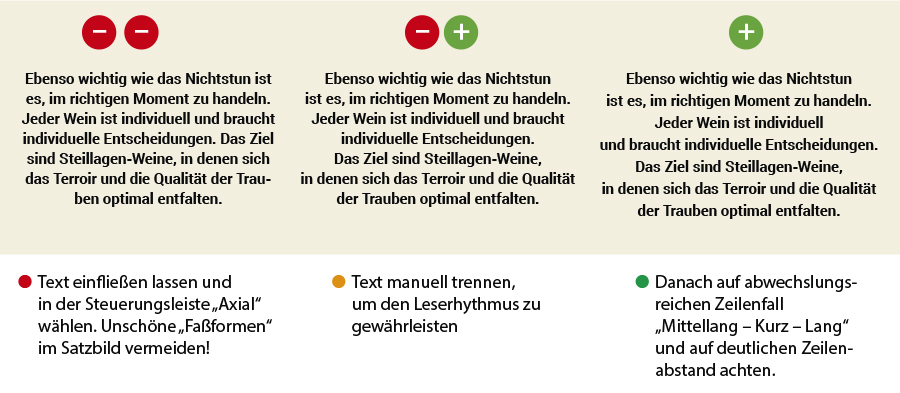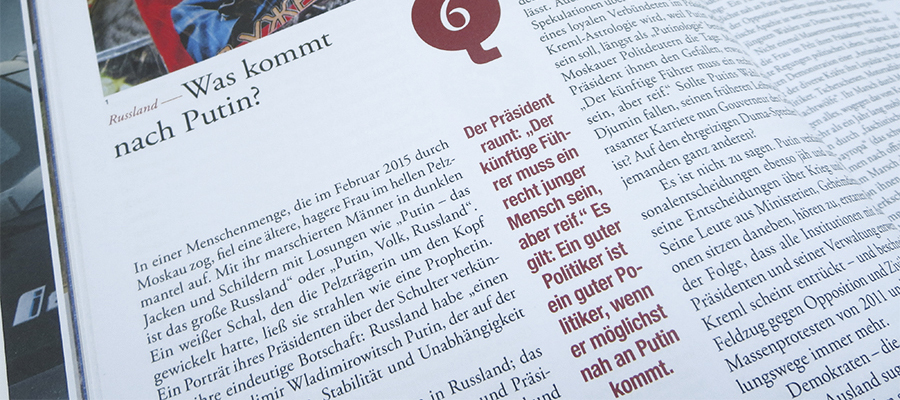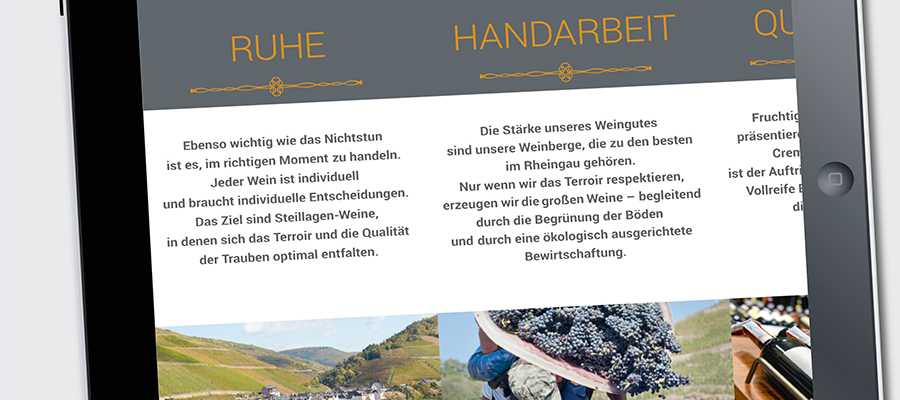
Typografie-Tipps: Axialsatz richtig anwenden und Zeilenfall optimieren
Axialer Zeilenfall in der Stuttgarter Opernzeitung
Ist Ihnen schon mal aufgefallen, dass die axiale Satzart wieder an Bedeutung gewinnt –insbesondere im Magazin-Design? Dabei dachte ich, die eher konservativ anmutende Satzart wäre seit den 70er-Jahren längst ausgestorben (in meiner Zeit als Schriftsetzer habe ich die Satzart oft angewendet, vor 30 Jahren erfreute sie sich großer Beliebtheit). Bis vor kurzem schien der axiale Satz der Gestaltung von Vereinsurkunden, Inhaltsverzeichnissen von Büchern oder dem Gedichtsatz vorbehalten. Aber nein, er ist wieder auf dem Vormarsch, wie das obige schöne Beispiel aus Reihe 5, dem Magazin des Staatstheaters Stuttgart, zeigt!
Dabei hat die Satzart auch durchaus ihre Berechtigung; bringt sie doch Aufmerksamkeit und Abwechslung ins Design. Aber Vorsicht: Bei der Anwendung des Axialsatzes sollten zugunsten der Lesbarkeit und eines ausgewogenen Satzbildes einige typografische Regeln beachtet werden.
Beispiele für axialen Zeilenfall
Gelungener Axialsatz in der Magazingestaltung für eine Tablet-App; Weingut Laquai
Beispiel gelungener Axialsatz in der Magazingestaltung für eine Tablet-App
Schön gestaltet, aber etwas schwierig zu lesen: Sinngerechtere Trennungen, zum Beispiel nach den Satzzeichen, hätten die Lesequalität deutlich verbessert; Quarterly, Frankfurter Allgemeine
Axialer Zeilenfall in einer Randspalte: Schön gestaltet, aber schwierig zu lesen.
Definition Axialsatz
Die korrekte typografische Bezeichnung ist Axialsatz oder axialer Satz. Er wird aber auch als zentrierter, symmetrischer oder Mittelachsensatz bezeichnet. Die Textzeilen werden durch eine gedachte Mittellinie im Satz- oder Layoutprogramm zentriert angewendet; wobei der Text natürlich zur linken und zu rechten Seite hin gleich lang ist.
Wo der axiale Satz angewendet wird
Um Abwechslung oder mehr Aufmerksamkeit zu erzeugen, wird der Axialsatz in der Regel bei Überschriften im Magazin-Design oder bei Headlines in Werbeanzeigen verwendet. Auch im Gedichtsatz findet der Axialsatz häufig Anwendung. In beiden Fällen unterliegt er dabei jedoch einem gewissen Leserhythmus. Für größere Textmengen ist der Axialsatz weniger geeignet, weil seine zentrierte Stellung einen ungestörten Lesefluss erschwert.
Typografische Regeln beim Axialsatz
Um beim Axialsatz einen schnellen und ungehinderten Lesefluss zu gewährleisten, sollten Sie die Satzstellung immer händisch korrigieren. Hier ein Beispiel, wie der Text in InDesign für eine Magazinseite automatisch erstellt und dann händisch bearbeitet wurde:
Zeilenfall optimieren: Händische Bearbeitung eines axialen Zeilenfalls
Praxis-Tipps: Wenn Sie mit der axialen Satzart arbeiten …
• Da der axiale Satz im Vergleich zu Flatter- oder Blocksatz schwerer lesbar ist, sollten Sie ihn in der Regel nur bei großen Schriftgrößen wie Überschriften und kurzen Einleitungstexten anwenden.
• Achten Sie bei der manuellen Nacharbeitung zunächst auf lesefreundliche Sinntrennungen des Textes. Tipp: Trennen Sie nach Satzzeichen wie Punkt, Komma, Gedankenstrich.
• Danach sollten Sie den Zeilenfall bestmöglich korrigieren nach dem Prinzip: Mittellang – Kurz – Lang (siehe Bild-Beispiel oben), um Abwechslung zu erzeugen. Vermeiden Sie unbedingt eigenständige Satzformen wie „Bierfässer“ und „Weingläser“.
• Achten Sie auf den richtigen Zeilenabstand. Je kleiner die Schrift und je größer die Satzbreite umso größer der Zeilenabstand. Dadurch gewährleisten Sie den Anschluss vom Satzende zur nächsten Zeile.